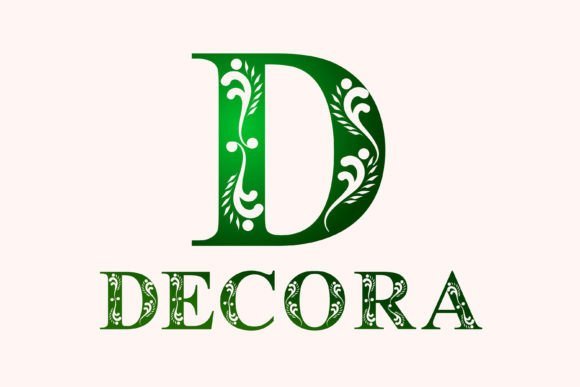
Decora Font
Decora Font – خط ديكورا
اجعل تصاميمك تنبض بالأناقة مع Decora Font، الخط المثالي للمشاريع الإبداعية والاحترافية. يتميز هذا الخط بتصميم أنيق وعصري يجمع بين الانسيابية والطابع الفريد، مما يجعله الخيار الأمثل للتصميمات الفاخرة، الشعارات، الدعوات، التغليف، والمحتوى الرقمي المتميز.
يشمل: حروف كبيرة وصغيرة، أرقام، ورموز مميزة.
الاستخدام: مثالي للعلامات التجارية، الإعلانات، الوسائط الاجتماعية، والمطبوعات الراقية.